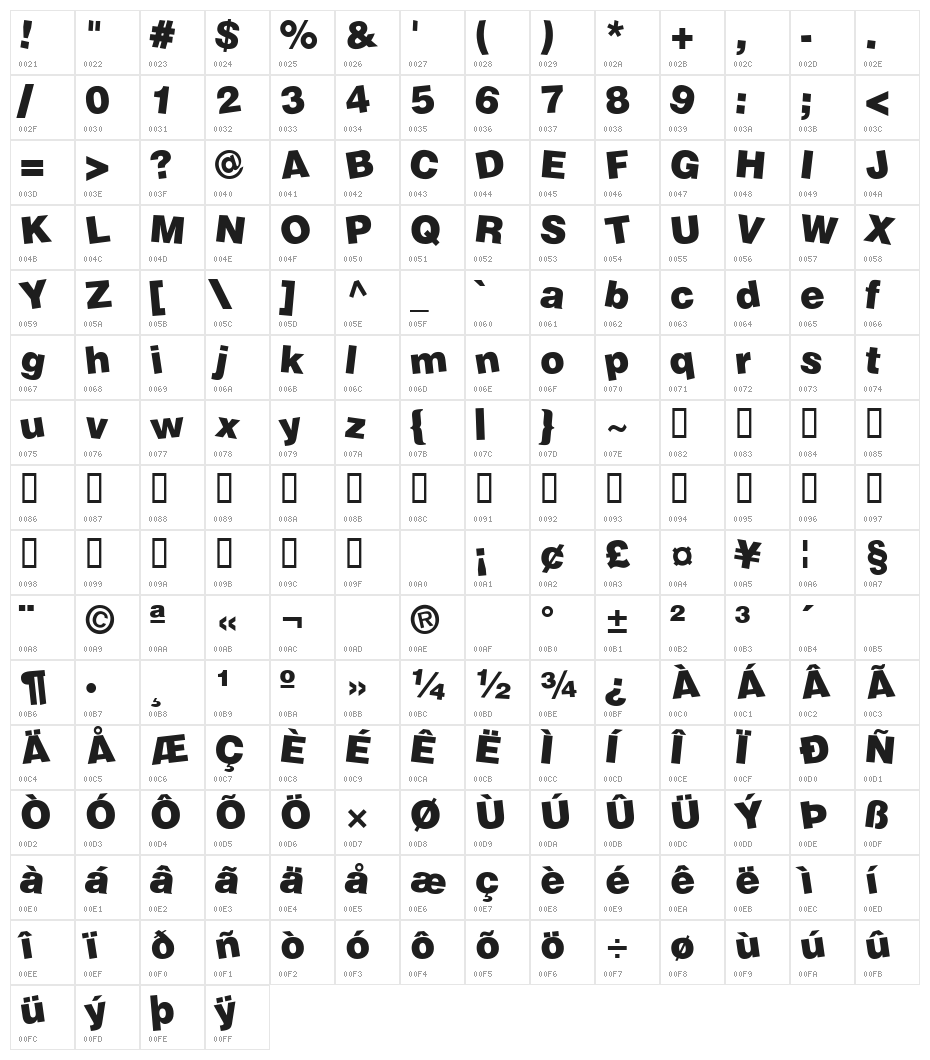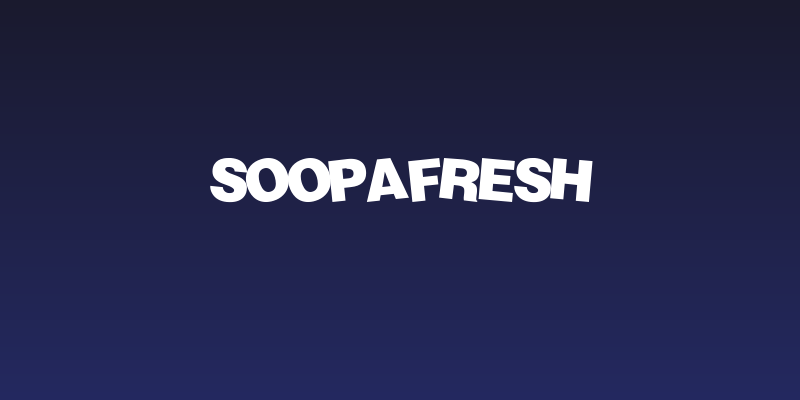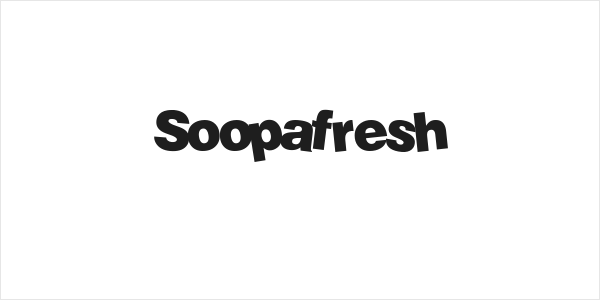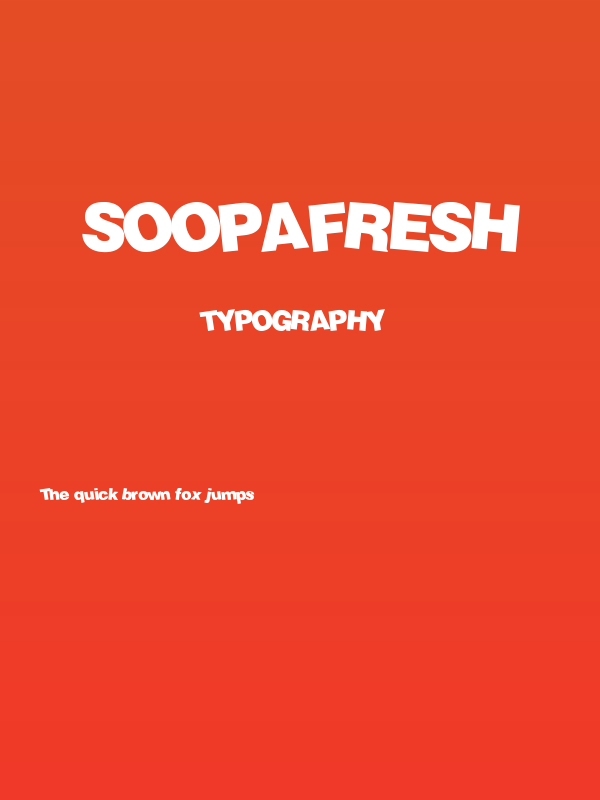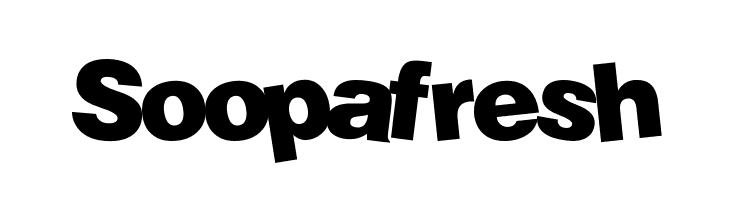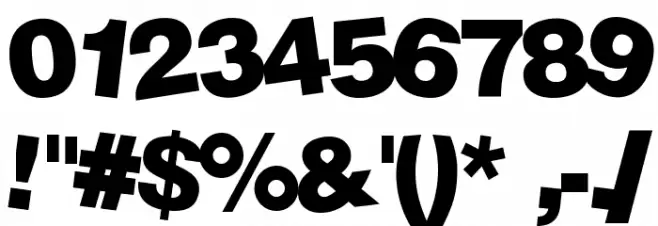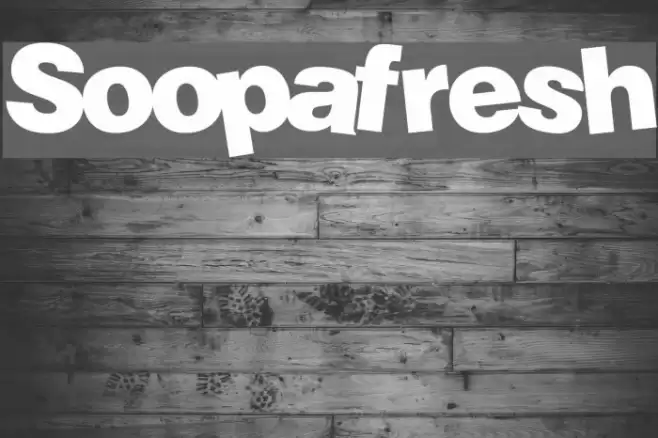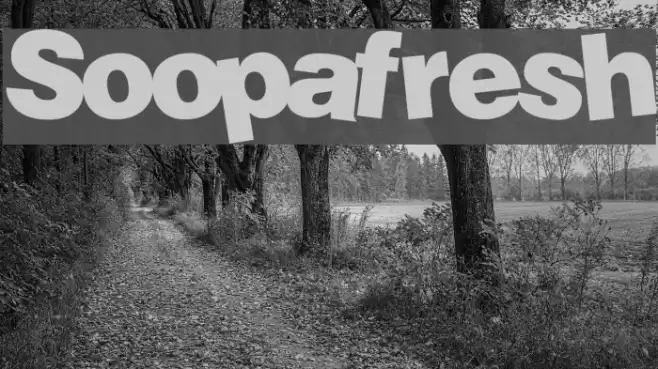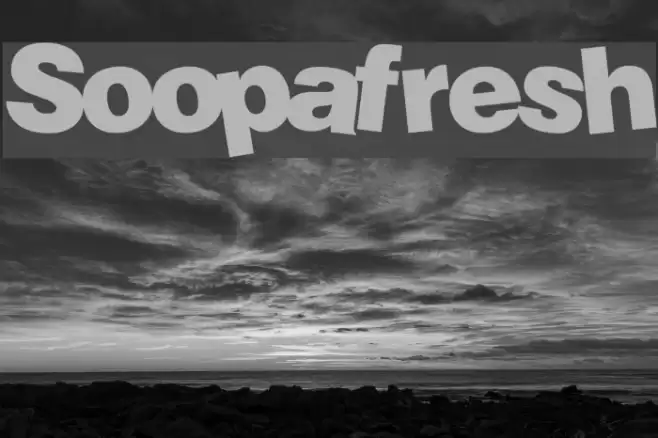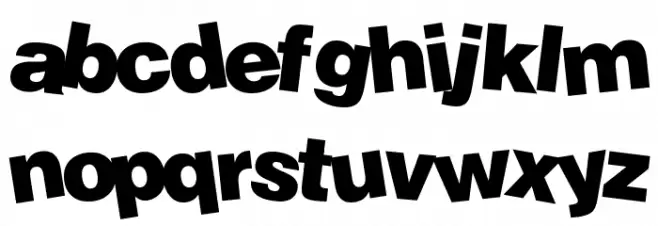
Soopafresh Font
| Stil general | Playful, Energetic |
| Caz de utilizare | Headlines, Posters, Branding |
| Proiecte propuse | Ideal for children's books, comic strips, playful branding, party invitations, and posters. |